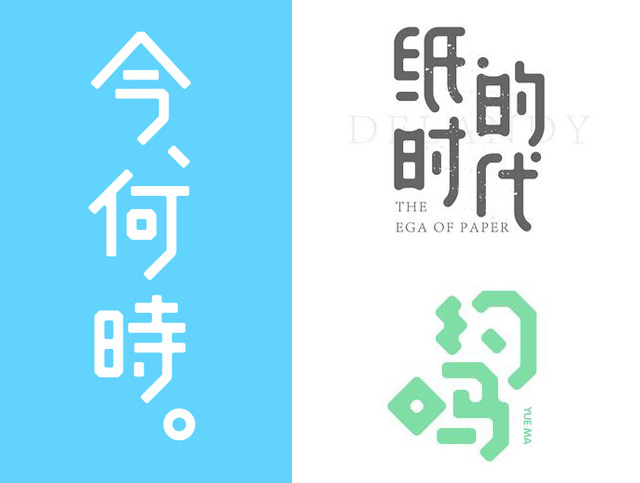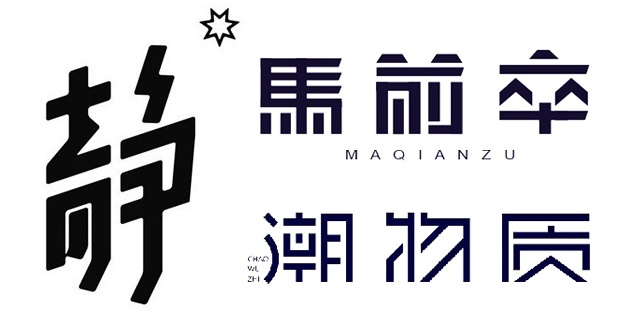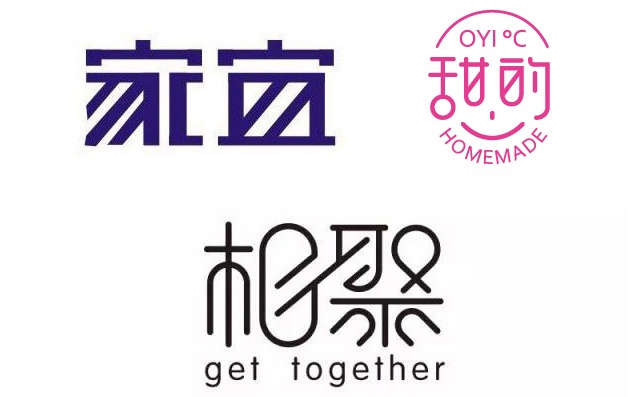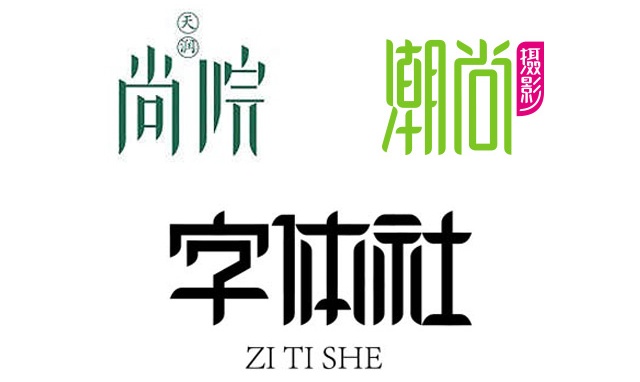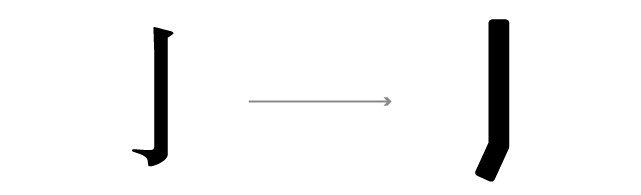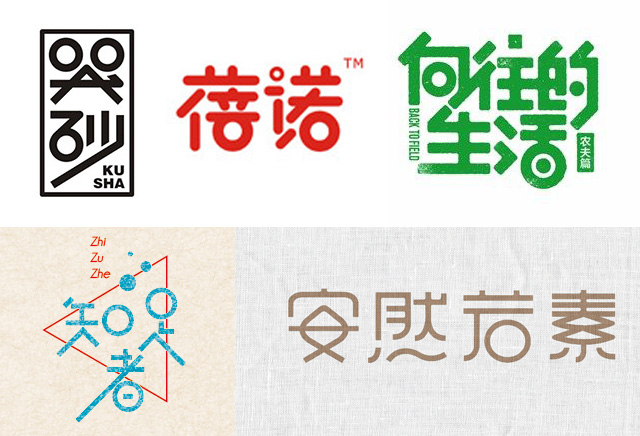
21种字体笔画的处理技巧!
这么做为了使文字笔画的形态更统一,也便于文字之间的笔画对齐。
把「日」部首变成两个同心圆
在象形字中「日」字的写法就是一个太阳,即在圆中加一个点,这种写法其实比现在的写法更简洁,更美观,自然会受到设计师的青睐。
把框内的横笔画用一个竖笔画取代
对于一些笔画比较多、结构比较复杂的字体,我们通常要做简化处理,比如说在一些含有日、目、月等部首的文字中,框内的横线就可以用竖线取代。
把框内的横笔画做成垂直倾斜处理
设计的字体太普通怎么办?我们要想办法刻意做一些变化,比如把包在框内的横笔画做垂直倾斜处理,就可以有效增加字体的设计感和动感。
把笔画端点的一个角做圆角处理
黑体字的笔画端点一般都是两个直角,而如果字体设计的需求是偏向优雅、女性的,那么直角的尖锐感就不太合适,把笔画端点中的一个直角处理成圆角效果会更好。
把竖钩变成竖折
把竖钩、竖弯钩、斜钩、弯钩设计成竖折,也是简化字体、增加设计感的有效技巧。
用圆替代「口」
口其实就是方形,从方形变成圆形也是一个简化的过程,可以使字体更加图形化。
给笔画增加一点小衬线
宋体字的笔画有衬线所以显得比较复杂,而黑体字的笔画没有衬线所以显得缺少细节,如果在黑体的基础上增加一点点衬线,即在笔画的端点处做一个小拐角,就能增加字体的细节,又不会显得过于复杂。
省略「口」部首的一条边
省略文字的某部分笔画是字体设计中经常会用到的技巧,由于口字是由四条边组成的方形,所以减去其中一条边也不会对其识别性有太大影响。
把「口」部首的底边或顶边处理成圆弧形
前面列举过把口设计成圆的做法,其实把口字的底边或顶边设计成圆弧形也有很好的效果。
用圆点或圆圈代替笔画「点」
这是很常见的一种笔画处理手法,可以有效增加字体的趣味性和对比。
把横笔画与位于其左上方或右上方的点连起来
这属于字体内部笔画连接的技巧,笔画端点靠得比较近的笔画自然更适合做连接。
把笔画交叉处做圆弧倒角
在圆体字的设计中,笔画的端点都是圆角的,所以如果把笔画交叉处也倒成圆角,整体风格会更统一、更温柔,也会给字体赋予一点中国风的韵味。
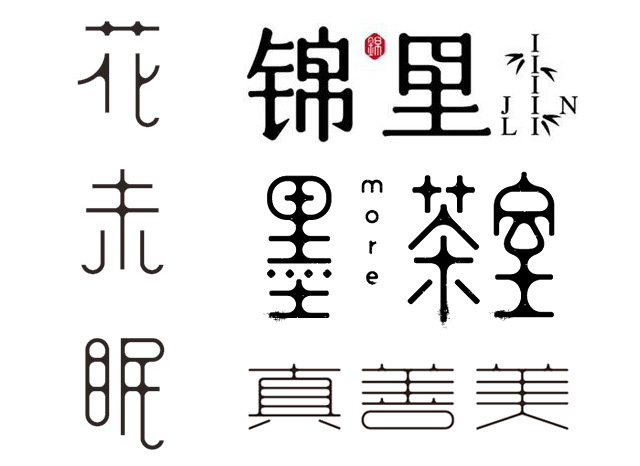
把撇和捺笔画处理成上宽下窄的效果
不同于宋体字中的撇和捺笔画一端较宽,一端则只有一个角的做法,而是在窄的这一头也保留一点厚度,只是厚度会比另一端要小很多而已,这种处理方式在偏女性的字体设计中用得比较多。
把八或人部首设计成向上的箭头
很多字体中都含有人或八部首,把它们简化成向上的箭头也可以增加字体的设计感与简约性。
把草字头转换成两个加号
其实就是把草字头从中间断开了,使其变成两株抽象的小草,既增加了字体的趣味性,也使其变得更丰富了。
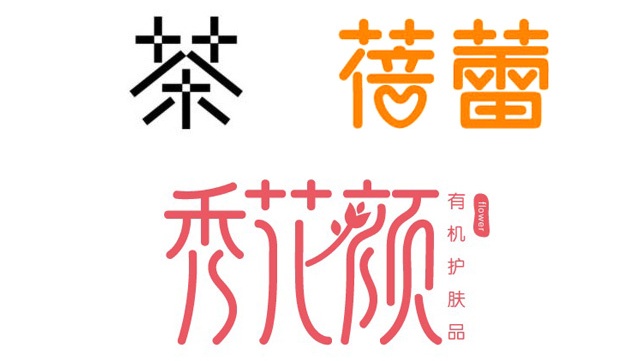
省略「尸」部首的左上竖笔画
为了使字体更透气、线条更流畅,字体中含有的「尸」部首常常会被做切割处理。
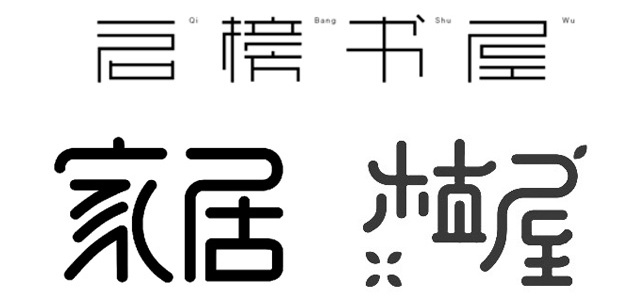
把部首「日」设计成回形纹
文字中的「日」部首只要经过简单的处理就可以变成回形纹,在手写字和中国风的字体中经常会用到。
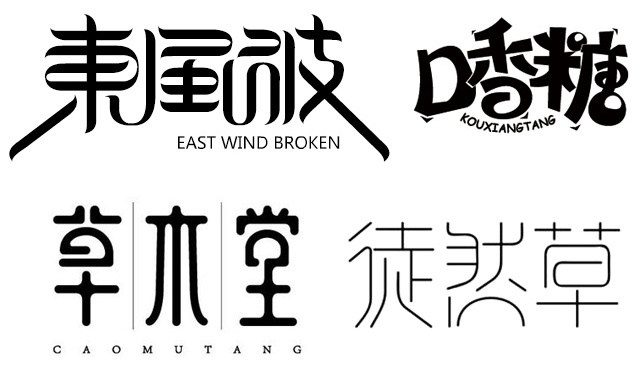
把单人旁简化成横折
这也是简化字体的做法,近似于把竖笔画右边的部分去掉了,只保留了左边的部分。
把四点水中的后三点连起来
印刷字体中的四点水都是独立的,所以显得有点散、有点繁杂,把后面的三点水连起来就可以解决这一问题,而且不会影响文字的识别性。
把口部首设计成菱形
把口部首设计成菱形一般是为了与文字中的其他笔画搭配起来更协调,比如谷字上半部分的笔画是倾斜的,而「口」部首的笔画是水平和垂直的,所以如果把「口」设计成菱形,在笔画的走势上会更统一。
结语
以上列举的这些字体设计小技巧,虽然都很常见且效果不错,但并不代表运用了这些小技巧就能设计出优秀的字体,就如上面列举的字体设计作品,都是在各方各面下足了功夫。无论怎样,字体的造型是否协调、美观,字体传达出来的调性是否紧贴设计需求才是最关键的。